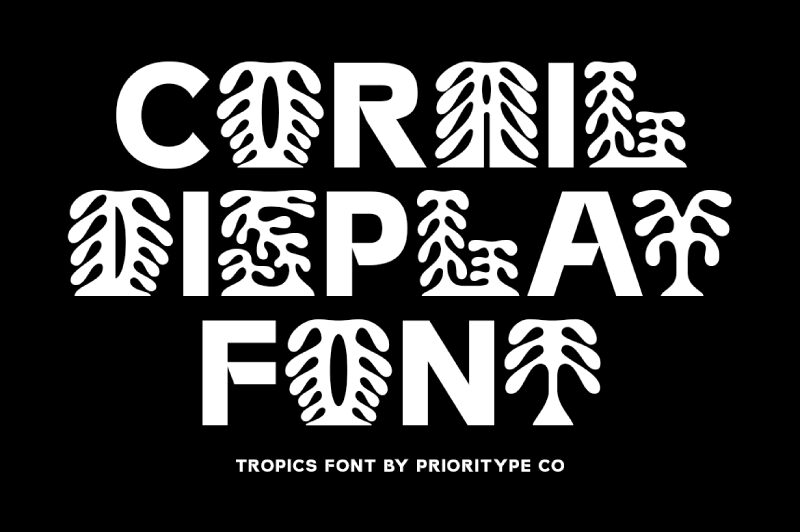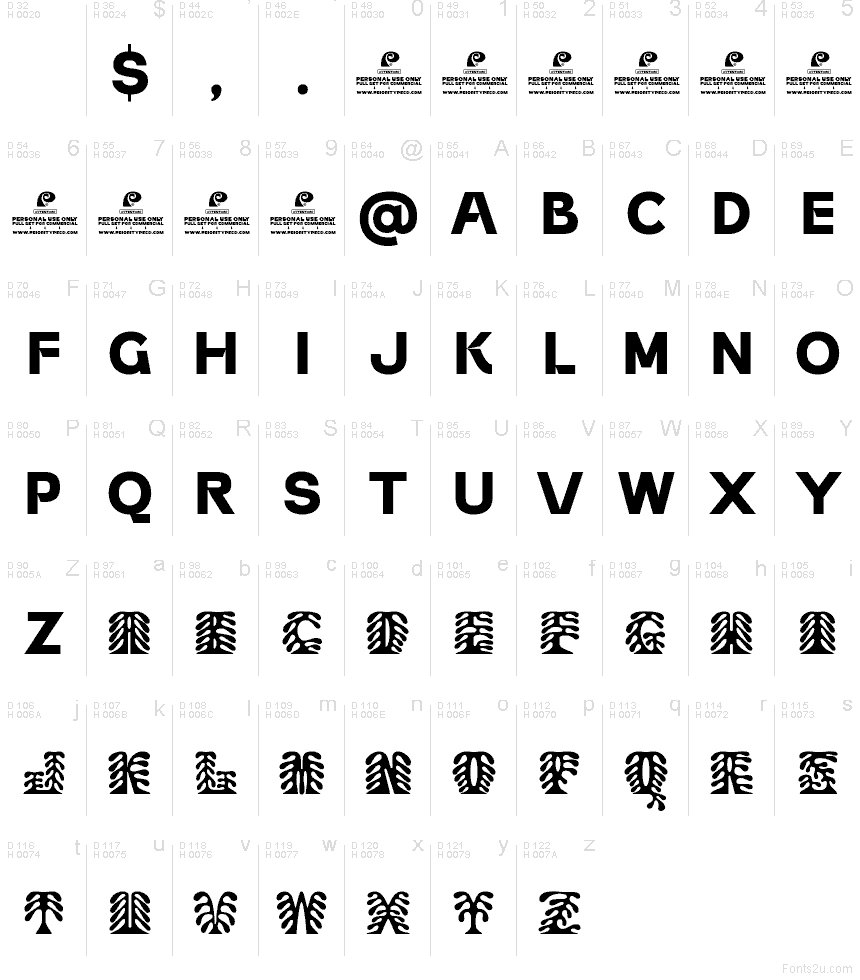
Prioritype Co.によるCorail Displayは、サンゴのような枝分かれした形状と丸みを帯びた切り抜きが特徴の、無料の装飾用ディスプレイフォントです。一つひとつの文字に有機的で植物のようなリズムが宿っています。ペンで書いたというよりも彫刻されたかのようなフォルムで、ゆったりとした曲線と繰り返される葉のモチーフが、セット全体を通してパターン化された輪郭を生み出しています。
Corail Displayは、ポスターのタイトル、イベント用グラフィック、アルバムアート、パッケージデザイン、そして力強いグラフィックラインを備えたボタニカルなアクセントが必要なブランドマークに最適です。この無料フォントは、招待状のヘッダーや装飾的なロゴにもぴったりで、サンゴに着想を得たその構造が、余計な装飾なしでもデザインをしっかりと引き立てます。